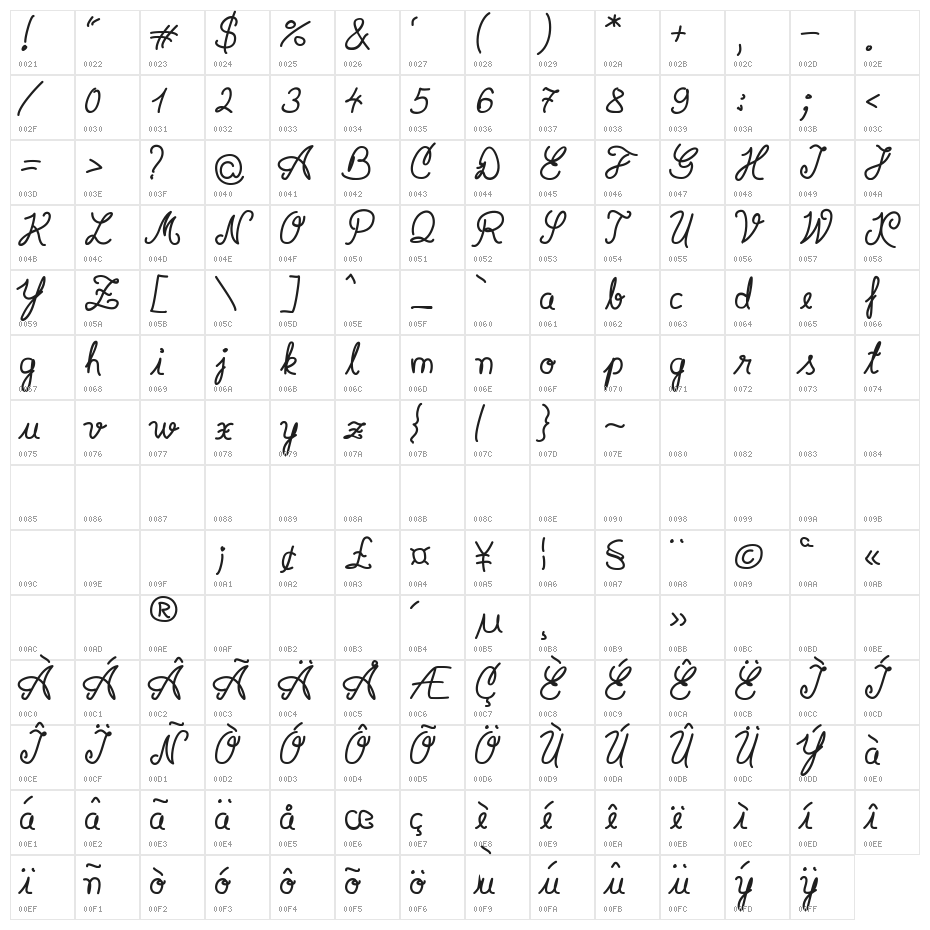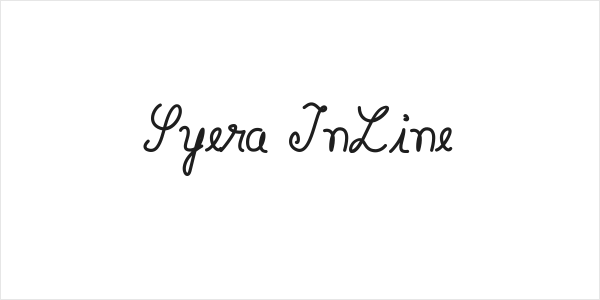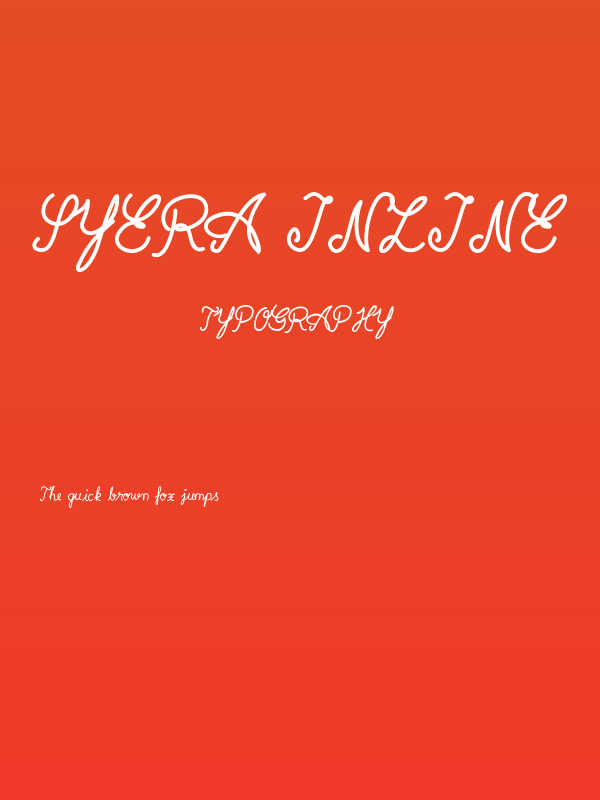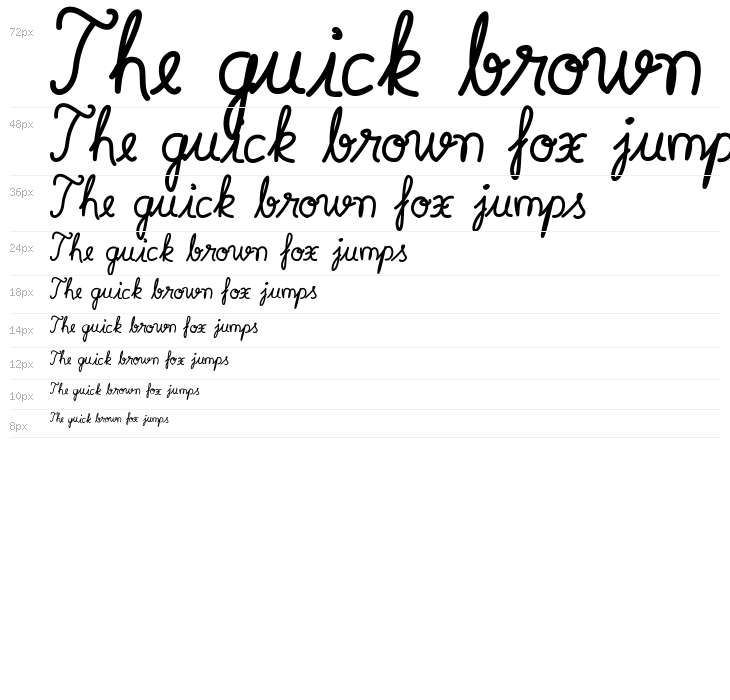
Syera InLine Font
| Estilo geral | Playful |
| Caso de uso | Logos, Invitations, Greeting Cards |
| Projetos propostos | Ideal for greeting cards, invitations, personal branding, and creative projects that require a friendly, informal touch. |